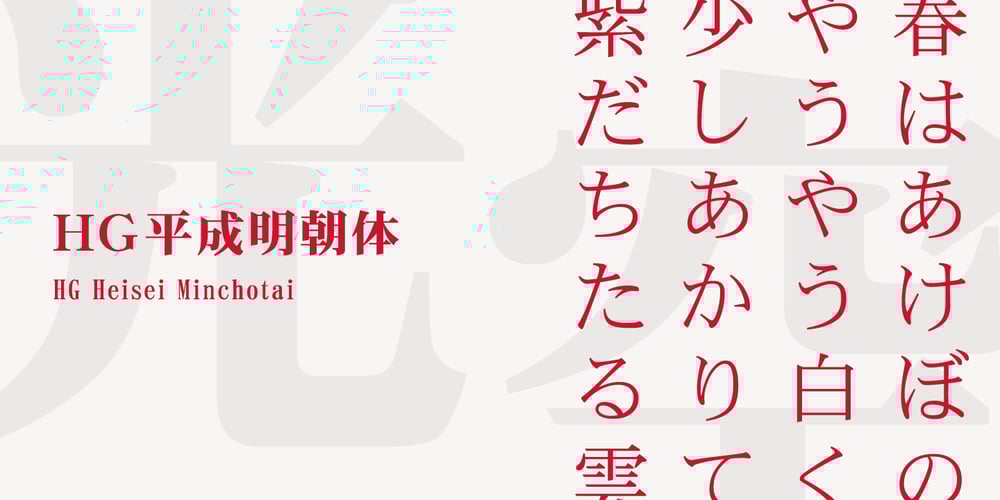
HG Heisei Minchotai
HG Heisei Minchotai font
HG Heisei Minchotai Font Family was designed by published by RICOH. HG Heisei Minchotai contains 1 styles and family package options. 平成明朝体は、ワープロやDTPの普及にともなうフォント需要の高まりに対して供給が遅れていたため、文字フォント開発・普及センターの指揮のもと、製作された、本文用の明朝体です。デザインは、リョービイマジクスが担当。横組み適性を考慮し、視覚的重心が低めになっています。可読性のため、ふところは広めに、また、低解像度出力機での使用を考慮し、直線を多用したシンプルなデザインになっています。